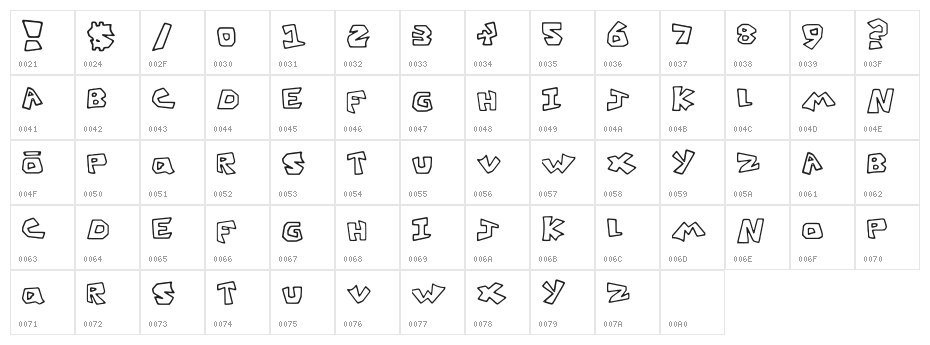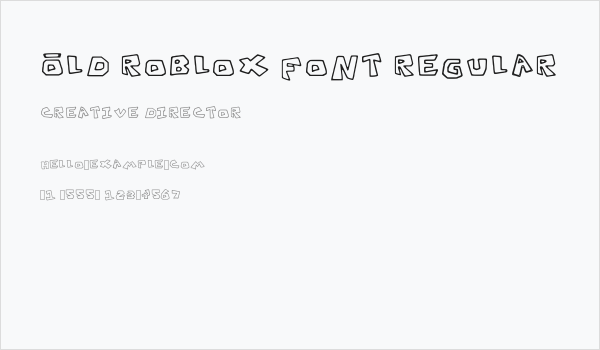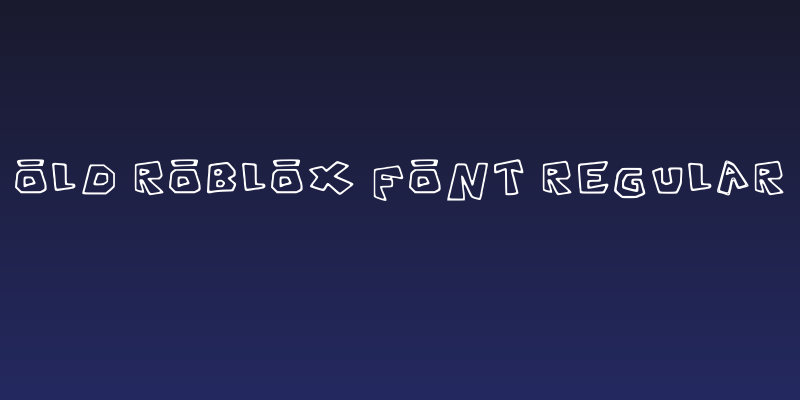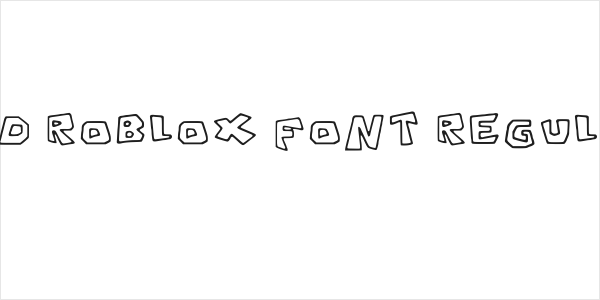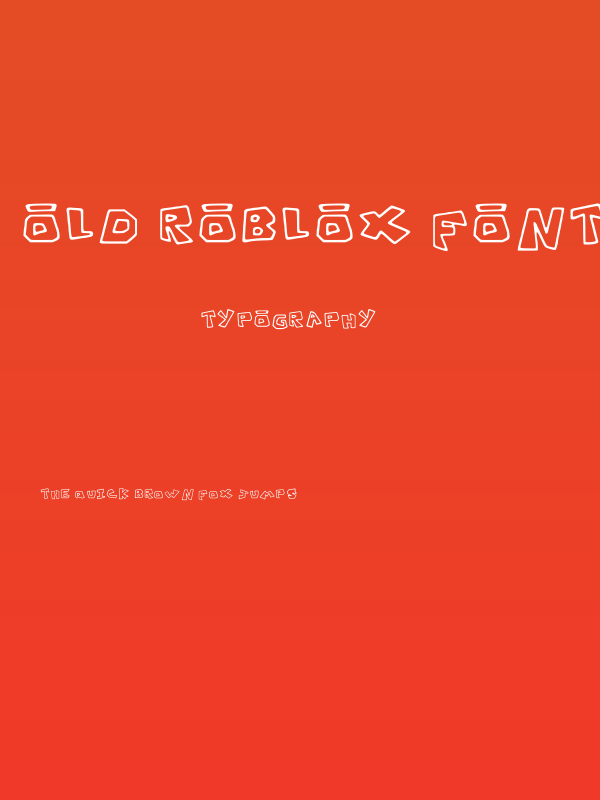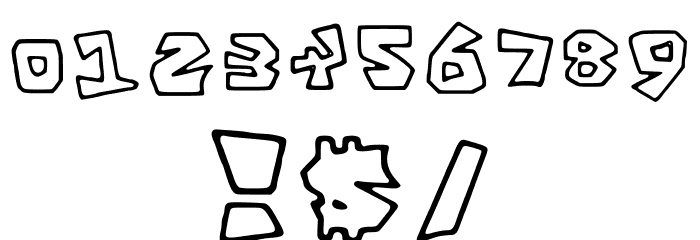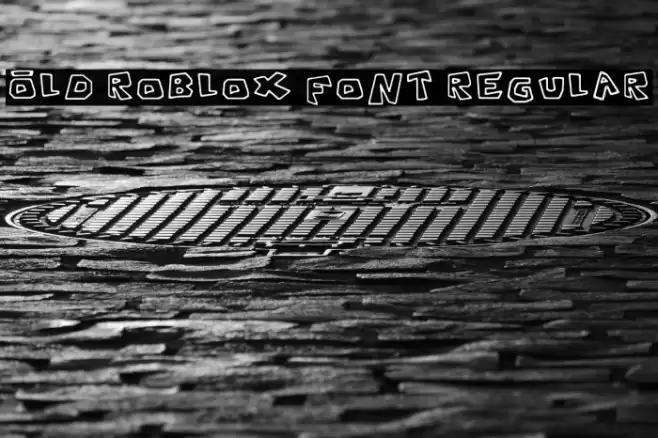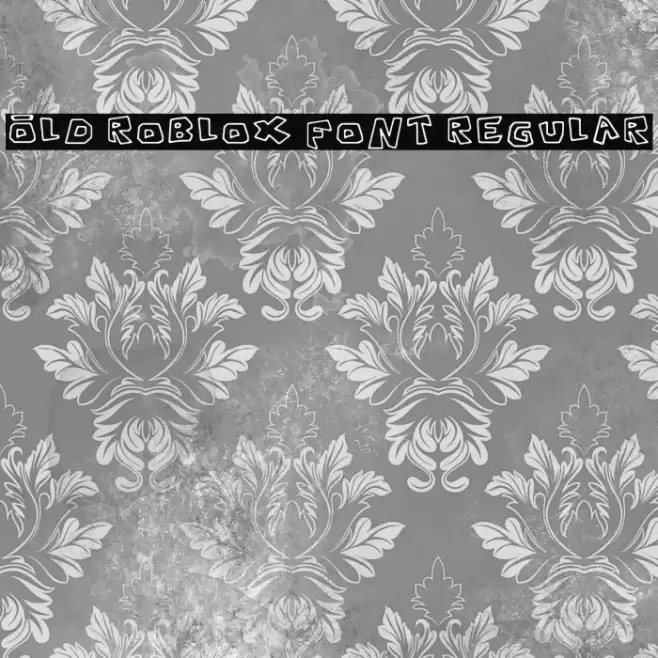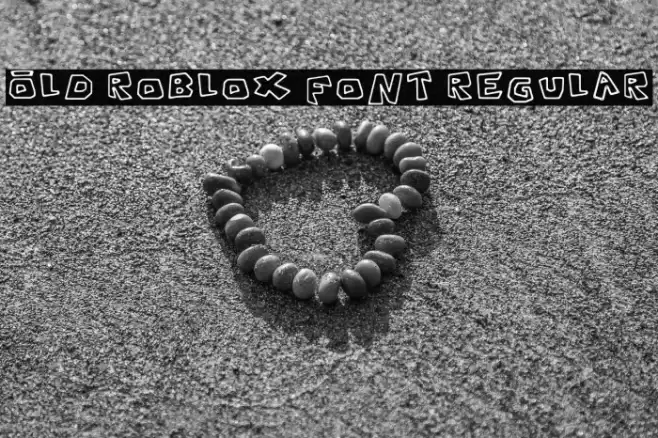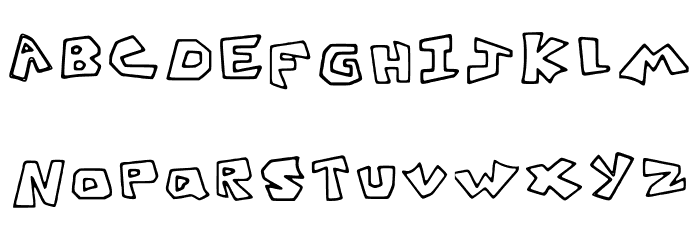
Old Roblox Font Regular Font
| Stile generale | Playful, Cartoonish, Hand-drawn |
| Progetti proposti | Ideal for children's books, comic strips, playful branding, and video game graphics. |